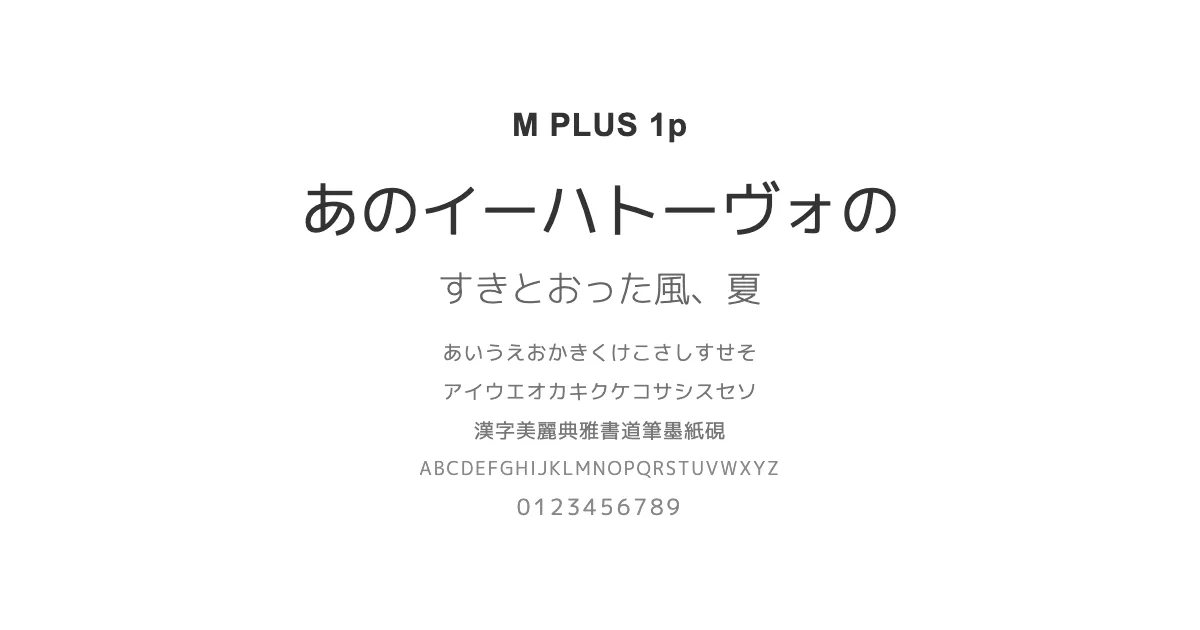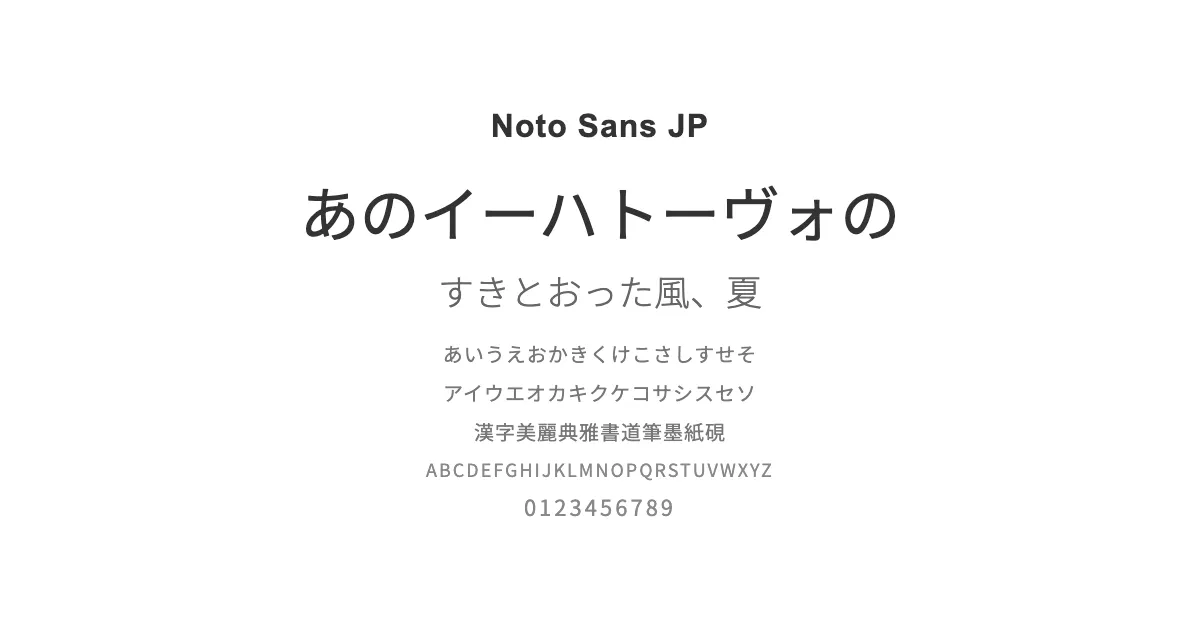
直線的でスタイリッシュな印象だが、親しみやすい雰囲気もあるゴシック体フォント。等幅でクセのないデザイン。
7種類のウェイトや欧文フォントまで対応した汎用性の高いゴシック体フォント。かな文字は丸みを帯びている。
使いやすさと読みやすさを重視して設計されたスタンダードなゴシック体フォント。ひらがなとカタカナが少し小ぶり。
「さわらびゴシック」と同様に本文用に開発され、可読性に優れた明朝体フォント。丸みのある柔らかいタッチとエレガントなスタイル。
かわいい手書きのような丸みを持ち、温もりを感じさせる丸ゴシック体フォント。イラストを使用したデザインと相性が良い。
シンプルでモダンなゴシック体フォント。視認性・可読性に優れ、多くの言語に対応。
すっきりとした曲線が特徴で、直線が多く、スタイリッシュな印象もある丸ゴシック体フォント。等幅でクセのないデザイン。
なめらかで深い丸みがあり、ナチュラルで優しい雰囲気の丸ゴシック体フォント。漢字の角が非常に緩やか。
レトロな雰囲気と毛筆のような流れるような柔らかさが特徴の明朝体フォント。漢字と曲線的なひらがなのバランスが美しい。
鉛筆やペンなどを使って書いた手書き風文字のような印象を与えるフォント。教科書体のようなデザインに近いので可読性・視認性に優れている。